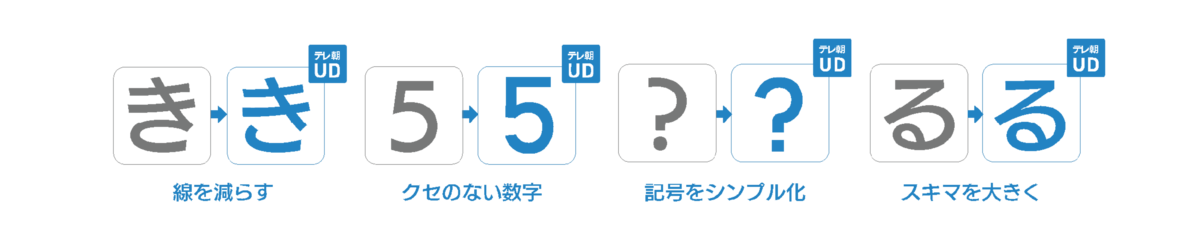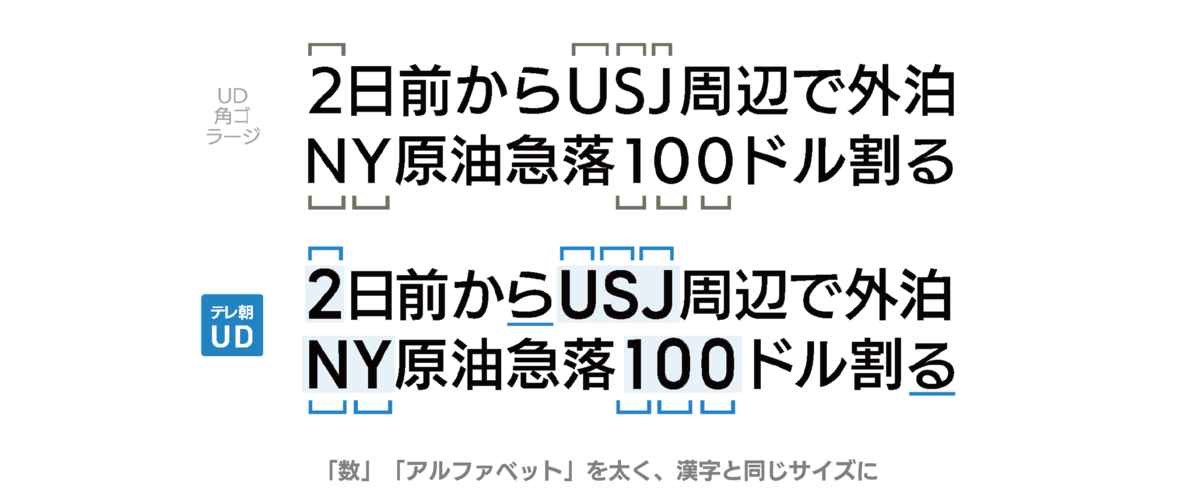
フォントワークス共同開発によるテレビ朝日オリジナルフォント「テレ朝UD」
フォントワークスは、テレビ朝日の報道情報番組に向けたオリジナルフォント「テレ朝UD」を共同開発・提供したことを2022年10月3日に発表した。
テレビ朝日のオリジナルフォント「テレ朝UD」は、テレビ朝日の長年の経験に基づくテレビテロップの知見と強いこだわりを、フォントワークスのフォント制作の技術で実現したオリジナルフォントとなる。
多様化が進む“デジタル映像メディア”の時代に合わせて、テレビ放送だけでなく、スマートフォン・タブレット端末など様々な画面サイズで文字の視認性を実現。
フォントワークスの「UD角ゴ_ラージ」をベースに、UD=ユニバーサルデザインの特性を活かしてテレビ朝日がデザインしたプロトタイプからフォントデータを作成。
デバイスを選ばない視認性の高さを追求した結果、様々なデジタルシーンにも適したフォントが完成した。
「テレ朝UD」書体の特徴
1.クセのないシンプルな文字
報道情報番組のフォントとして、視認性の向上にそぐわないと判断した“表現”を徹底的に排除し、文字の“見分けやすさ”を最優先に、ひらがな・カタカナ・数字・アルファベット・記号のいずれにおいても、シンプルで見やすい文字を追求した。
2.文字の画数による濃淡を低減
日本語表現には、画数の多い漢字と形がシンプルで画数の少ない英数字が混在するため、濃淡の問題がある。漢字と英数字のサイズを“対等”にすることで、濃淡の見え方の差を解消し、オリジナルフォントでしか実現し得ないデジタルシーンに最適な“バラつきのない視認性”を実現した。
3.デジタル時代の明瞭な「数字」
報道分野でとりわけ重要な情報となる「数字」については、とくに可読性の高さを追求し、詳細に検討を重ねた。単体の数字でも桁数の多い数字でも、フラットかつ均一な読みやすさで、瞬時に数値を認識できるデザインを実現している。